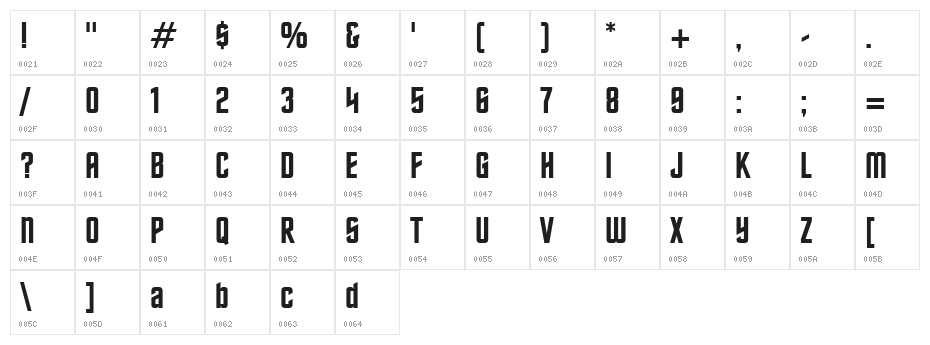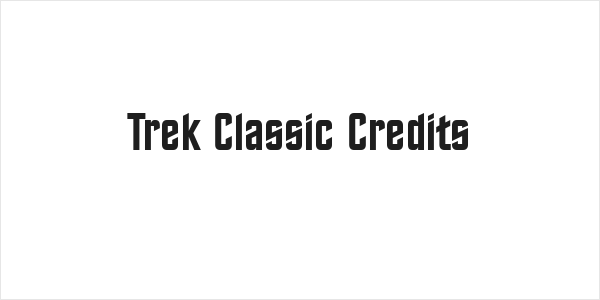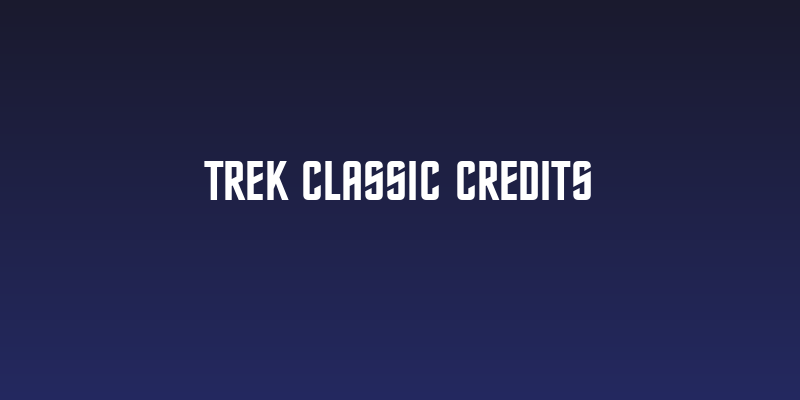
Trek Classic Credits Font
| Stil general | Futuristic |
| Proiecte propuse | Ideal for sci-fi themed designs, movie posters, video game graphics, and branding that requires a modern and bold aesthetic. |